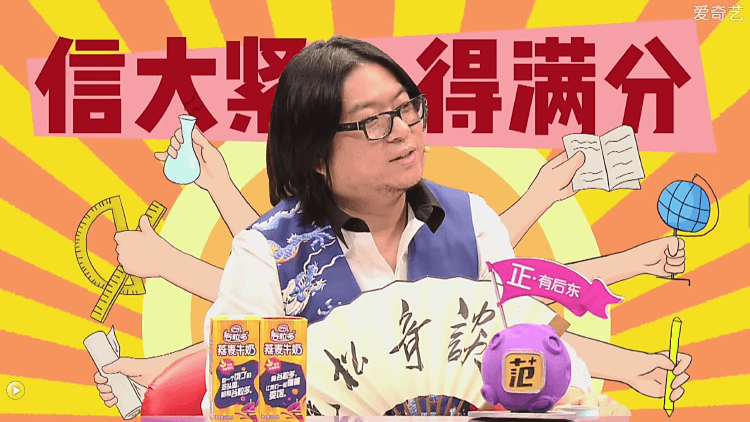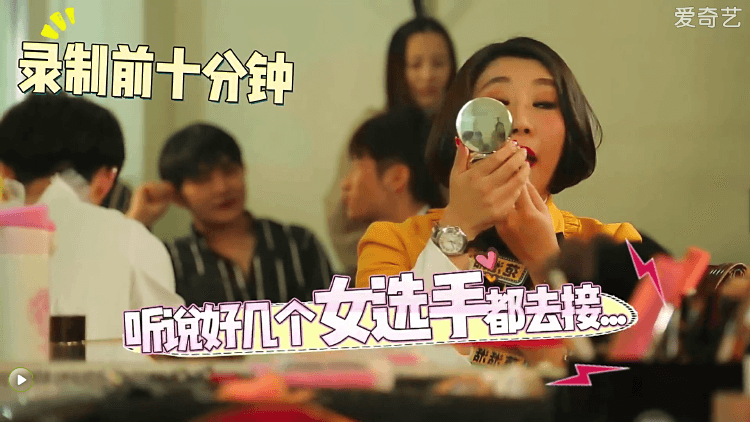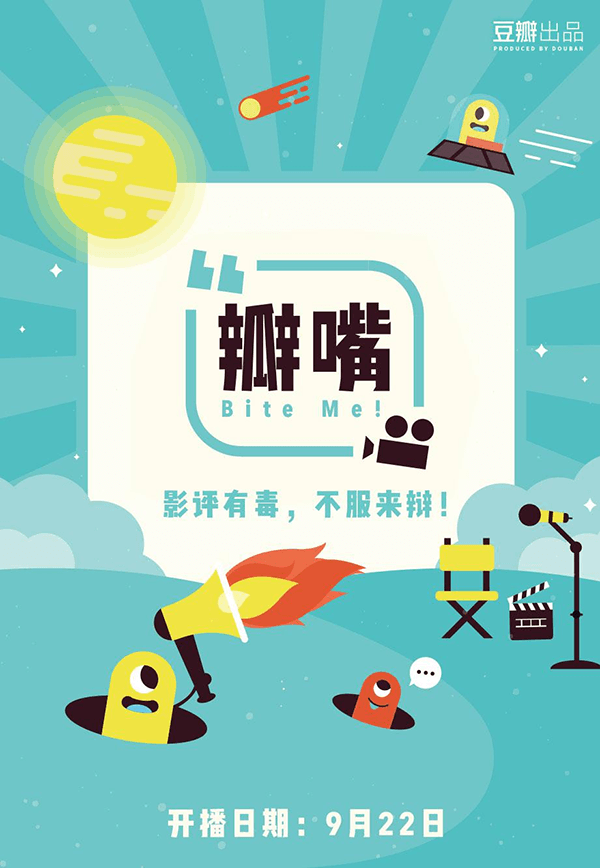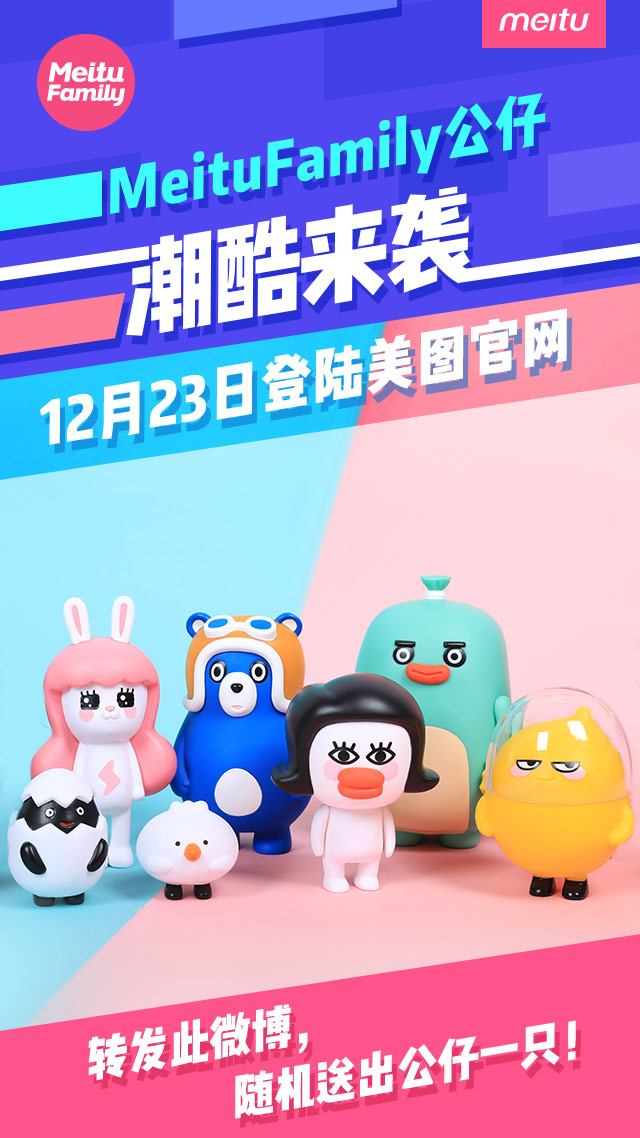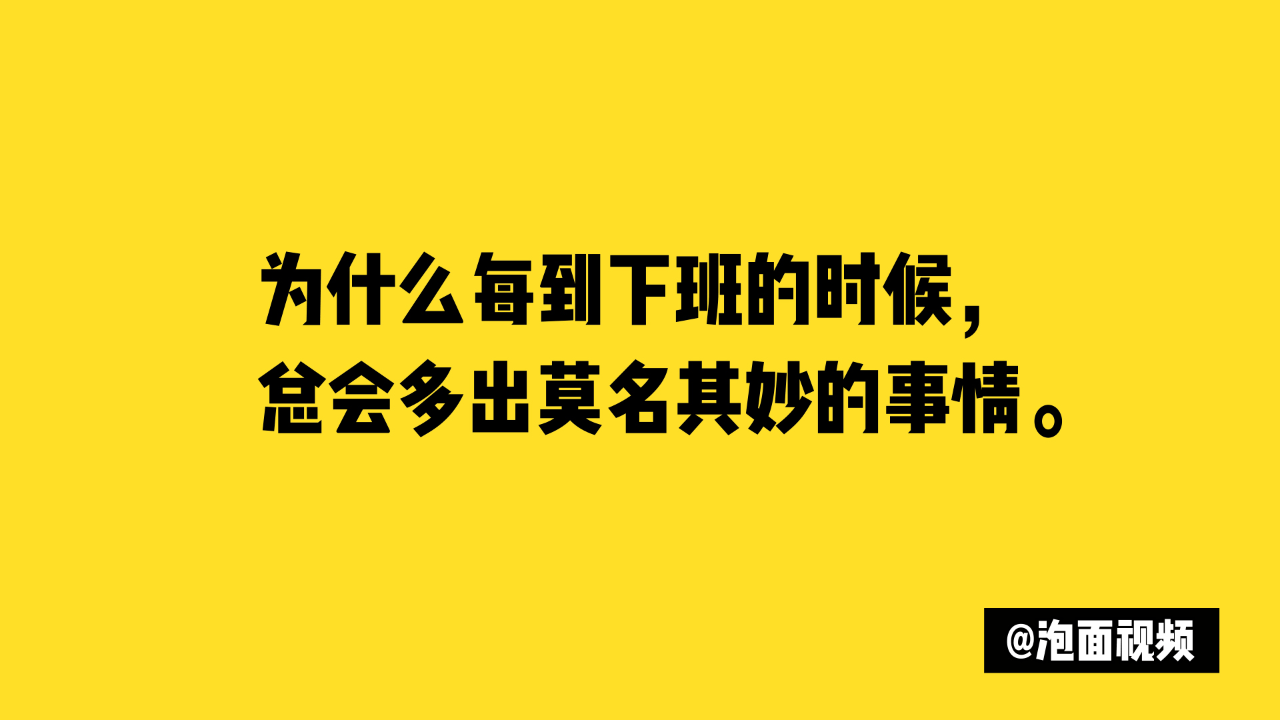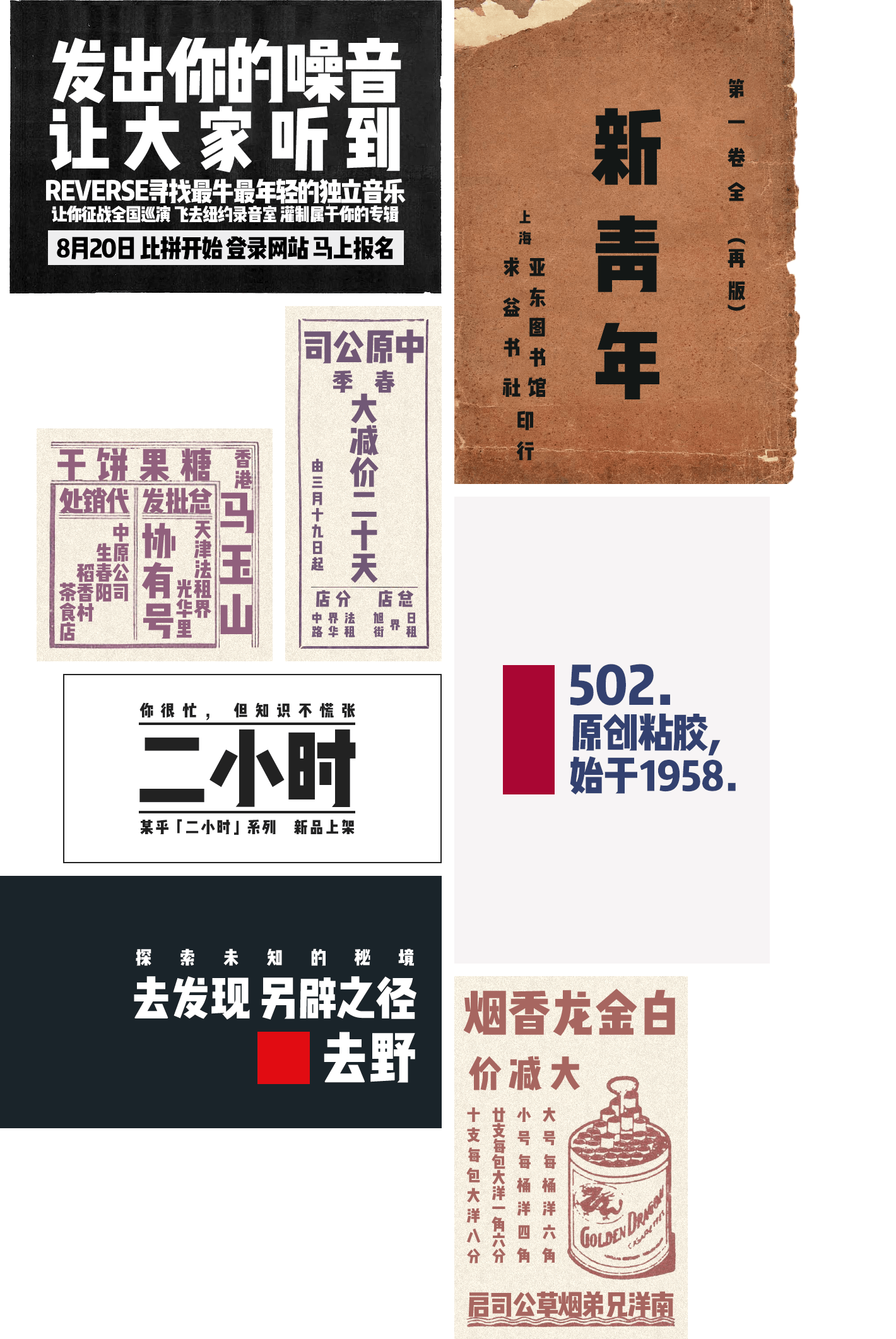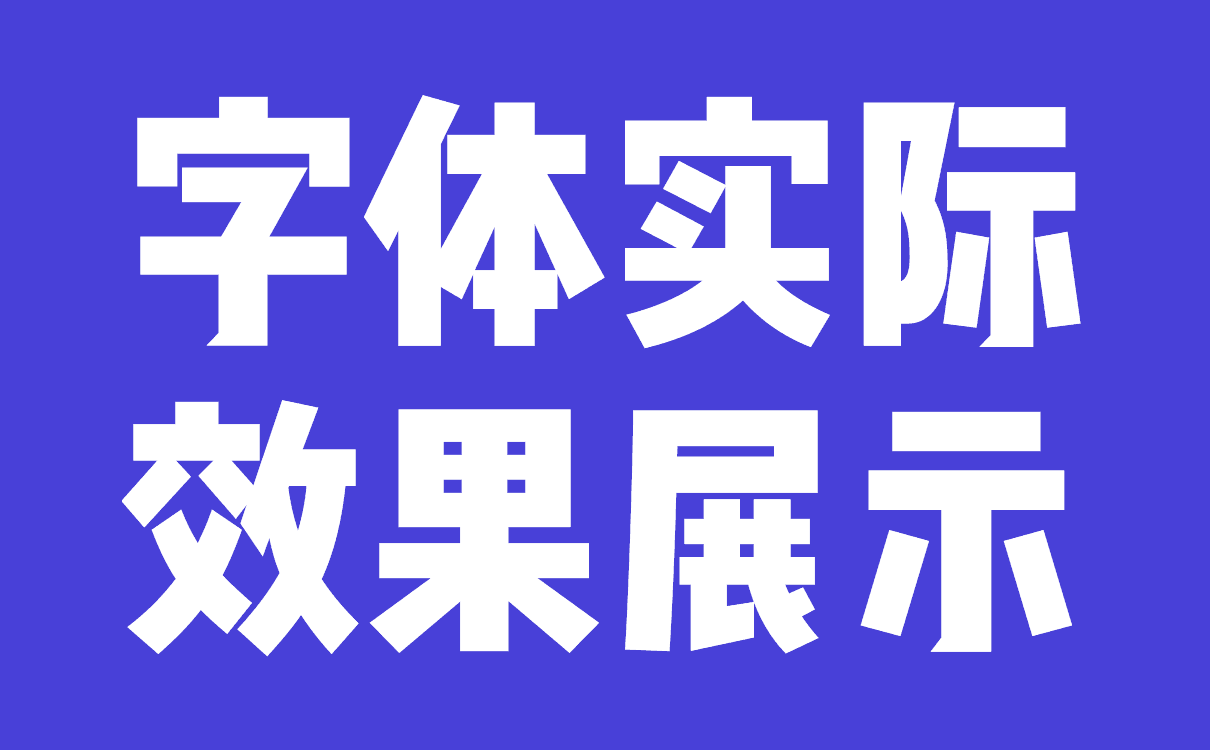
文悦新青年体
「文悦新青年体」源自二十世纪的美术字设计,结合了包括创刊于 1915 年的《新青年》杂志书名字标的设计风格。字型上融合新旧两种元素,将忆古情结表现得淋漓尽致的同时,又能相得益彰地展现出现今社会所需的极强表现力。
「文悦新青年体」相比市面上的其他美术黑体,有着更加鲜明的视觉形象,能帮助设计者更立体地向受众传达出品牌理念,在满足信息传播功能性的同时,让品牌的调性展露无遗。
使用实例
样张
风格复古并不代表使用场景受限,相反,沉淀百年的爆破力一触即发。
使用实例
首发客户
《奇葩说》是一档由米未传媒和爱奇艺打造的脱口达人秀,节目由马东主持,并邀请了蔡康永、金星、高晓松担任导师,旨在寻找华语世界中,观点独特、口才出众的最会说话的人。因节目宗旨与产品气质的奇妙关联,2016 年 3 月「文悦新青年体」首发亮相《奇葩说》第三季。